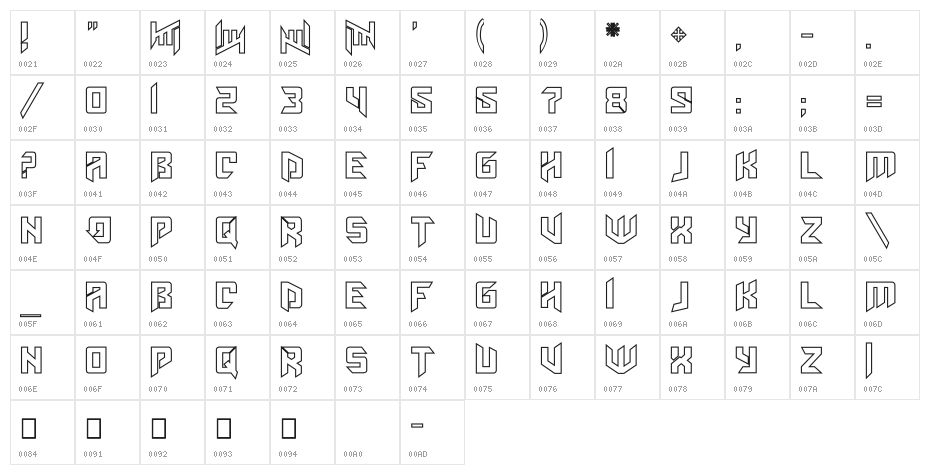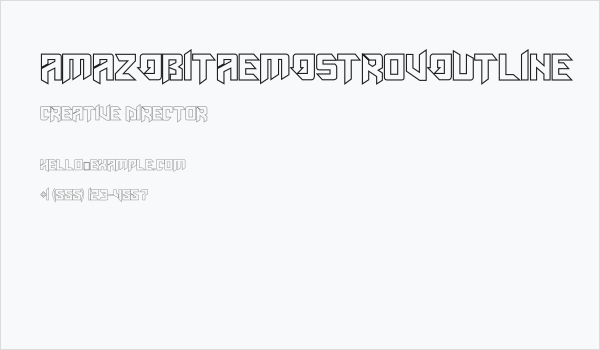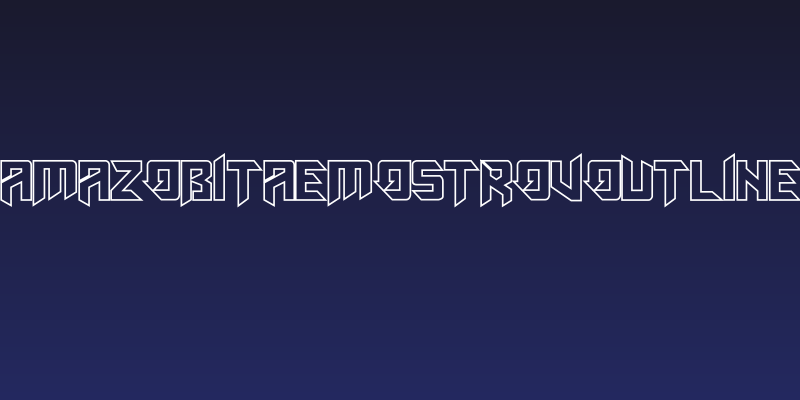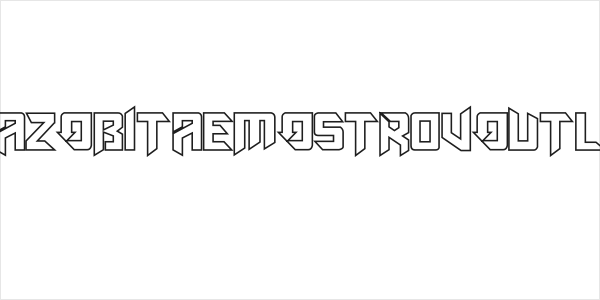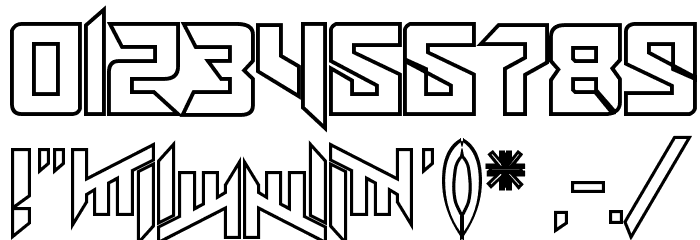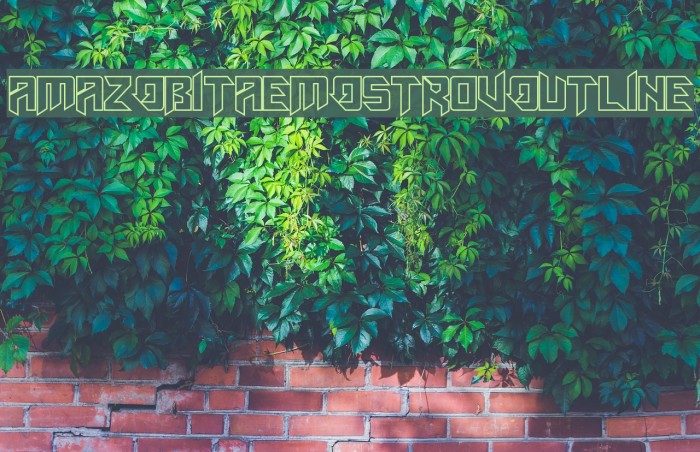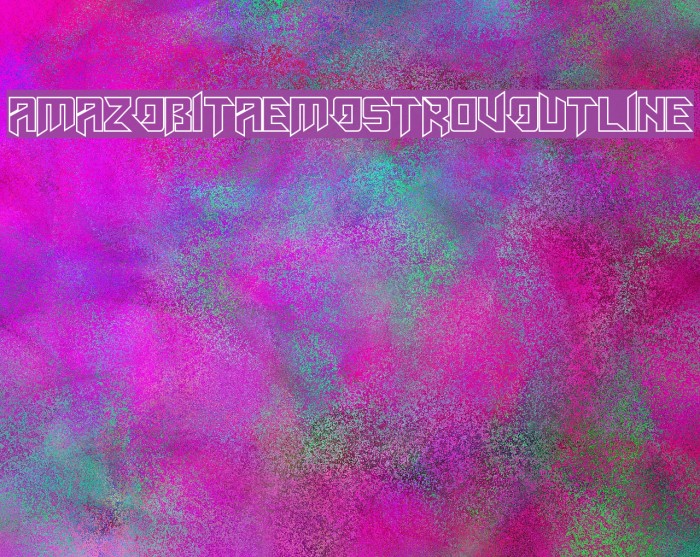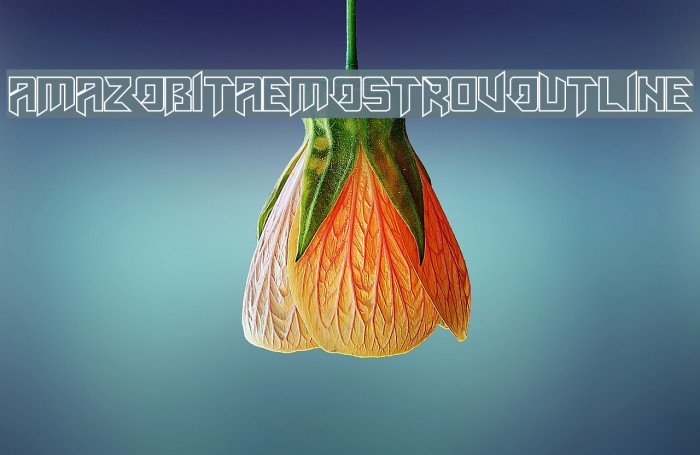
AmazObitaemOstrovOutline Font
| Progetti proposti | Ideal for sci-fi themed designs, video game titles, posters, and branding that requires a modern and bold statement. |